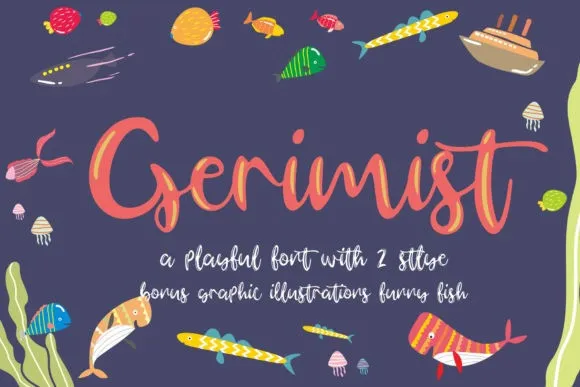
Gerimist Playful Font – Download Grátis
Gerimist Playful Font é uma elegante escolha para designers que desejam adicionar um toque descontraído e único a suas criações. Esta fonte script, desenvolvida pelo designer Hamilton, oferece linhas únicas e alternativas de caracteres, tornando-a perfeita para um uso natural e autêntico no design de uma maneira que parecia ter sido escrita a mão. Suas características incluem o estilo gracioso da tipografia script combinado com uma leve ironia dos traços, criando um resultado encantador e natural. Com seu formato de display único e encantador, Gerimist Playful Font se destacará em uma ampla variedade de ambientes e aplicações, do design de camisetas a criação de cartões de boas-vindas. Se você está procurando por inspiração criativa para criar algo inovador, esta fonte é um ótimo ponto de partida. Com ela, você pode explorar novos limites na sua arte e design, seja em mugs, camisetas ou até mesmo em cascas de telefone. Gerimist Playful Font é uma adição perfeita para coleções de fontes modernas e divertidas, oferecendo um ar de versatilidade que vai agradar a qualquer designer. Estamos ansiosos para ver o quanto você pode criar com ela!